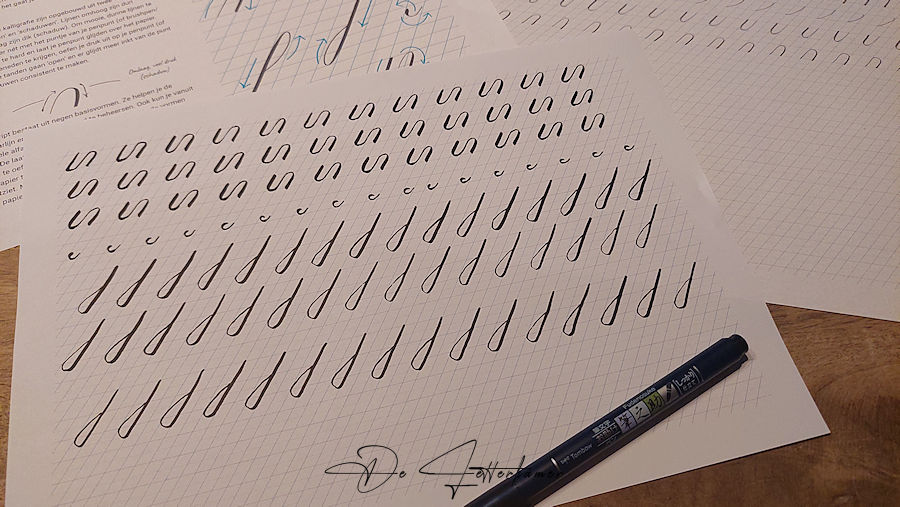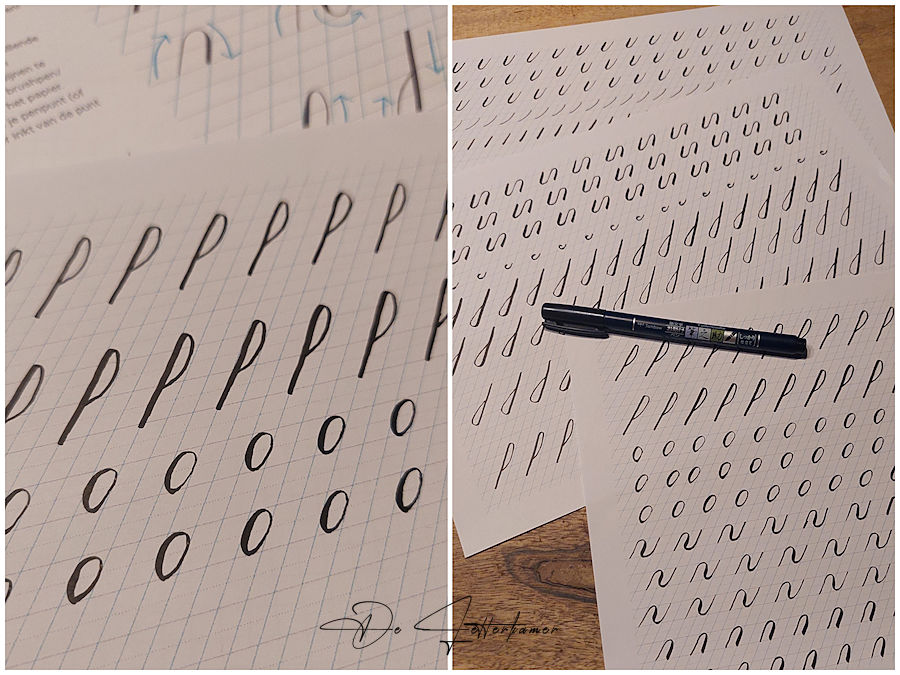
Hier zijn we terug, even een stop ingelast, en we reizen weer verder in de wondere wereld van kalligrafie, er heerst een stukje geschiedenis rond, ik kon het niet laten om even te lezen, een 1ste deel, kort samengevat:
In het Westen:
In Europa werd kalligrafie aanvankelijk uitgevoerd door slaven in het Romeinse Rijk en later door monniken in kloosters. In de late middeleeuwen ontstonden gilden van kalligrafen en verluchters. Belangrijke stijlen zijn Gotisch, Romaans, Karolingisch en Beneventaans.
Kalligrafie is de kunst van het schoonschrift.
Eerst ga ik mijn hand opwarmen, het is nodig. Het moet, eigenlijk. Enkele basisvormen heb ik eerst met potlood gedaan. Van een zachte naar een harde lijn en omgekeerd. De druk oefenen vooraleer ik start.
Nogmaals deze basisvorm geoefend, die lus vind ik het moeilijkste.
Nee, automatisch gaat het nog niet, ik moet nog teveel nadenken. Ik vermoed dat het nog weken misschien wel maanden gaat duren.
Hierbij ook de andere basisvormen geoefend.
Om die lus mooi afgerond te krijgen, vind ik best wel een moeilijke taak. Links naast mij mijn pc, een film aan het afspelen, die ik al verschillende keren heb gezien, staat er gewoon als gefluister af te spelen, niet meer en niet minder.
Het uurtje was vlug voorbij, het gaat wel beter, toch nog steeds goed opletten met het uitoefenen van de druk. Zacht naar hardere druk en omgekeerd. Als ik woorden zal schrijven, denk ik al bij mezelf, dit komt nooit goed. Blijven oefenen zegt men. Het valt me wel op, dat Nederlanders er meer mee bezig zijn dan Vlamingen. Ik vind bijna niks in de buurt qua lessen en informatie, steeds kom ik in Nederland uit. Zo dichtbij ook in taal en toch veraf lijkt me.